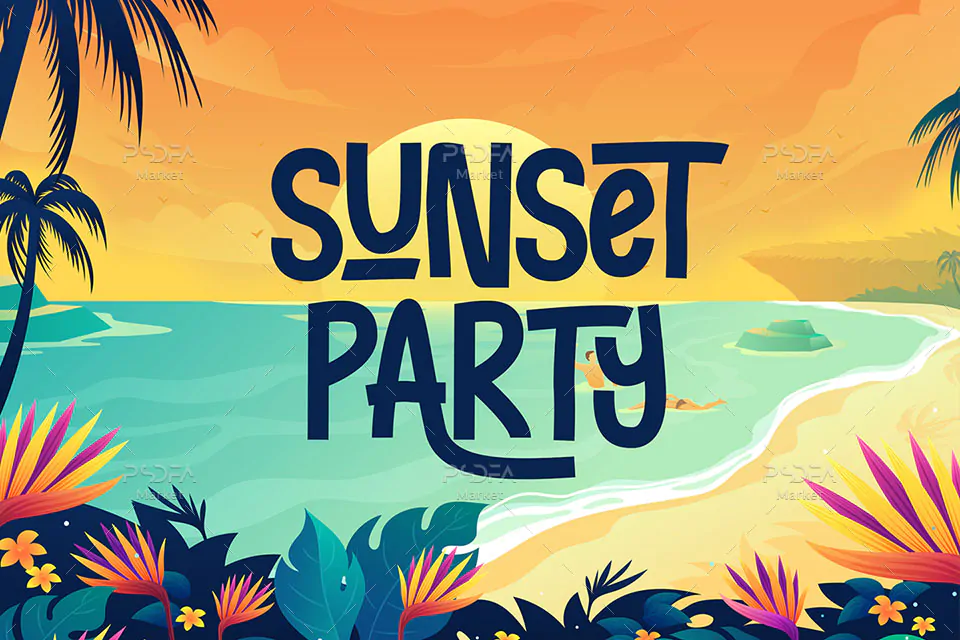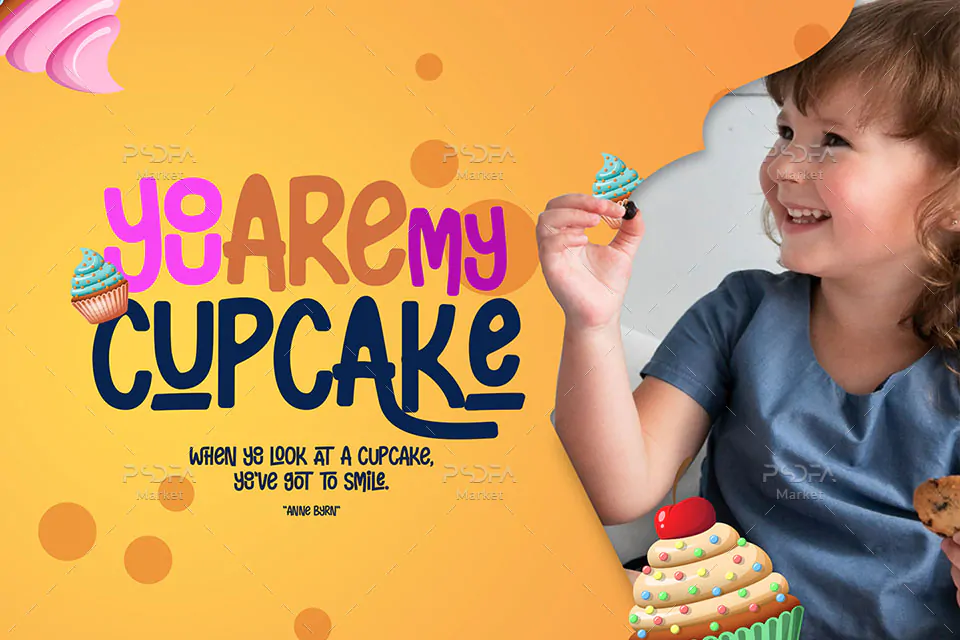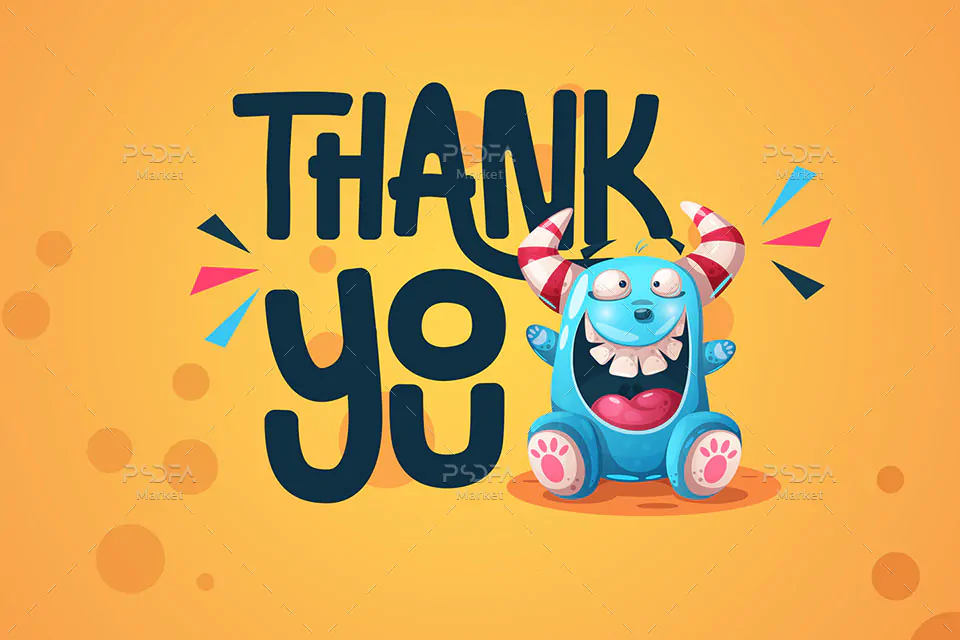
فونت نمایشی فانتزی و کارتونی Naughty Monster یک قلم فوق العاده زیبای انگلیسی است که میتوانید از آن در طرحهای گرافیکی خود استفاده کنید. این فونت در قالب فایلهای OTF, TTF, WOFF بر روی سایت بارگذاری شدهاند که با نصب یکی از دو فرمت ttf یا otf در پوشه فونتهای سیستم قادر به استفاده از آن در تمام نرمافزارهای گرافیکی و ویرایشگر متن همچون فتوشاپ، ایلاستریتور، ایندیزاین، مجموعه نرمافزار آفیس و … خواهید بود.
فونت Naughty Monster در وزن معمولی (Regular) طراحی شده است که میتوانید از آن در طراحی انواع کارت تبریک، کارت پستال، کارت ویزیت، طراحی انواع بنر یا پوستر، تراکت، تقویم و دیگر طرحهای گرافیکی استفاده کنید. همچنین نسخه وب فونت این قلم زیبا نیز در فایل فشرده قرار دارد که مناسب جهت استفاده در طراحی صفحات وب میباشد.